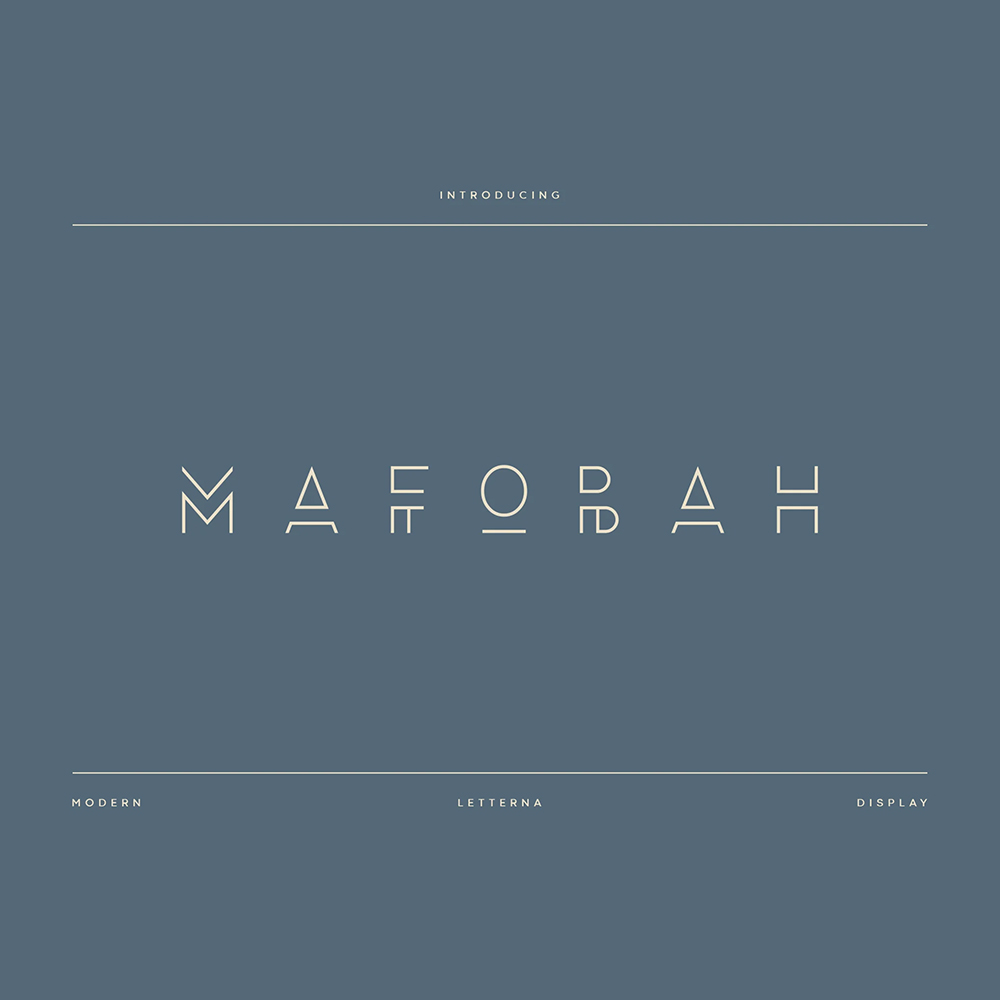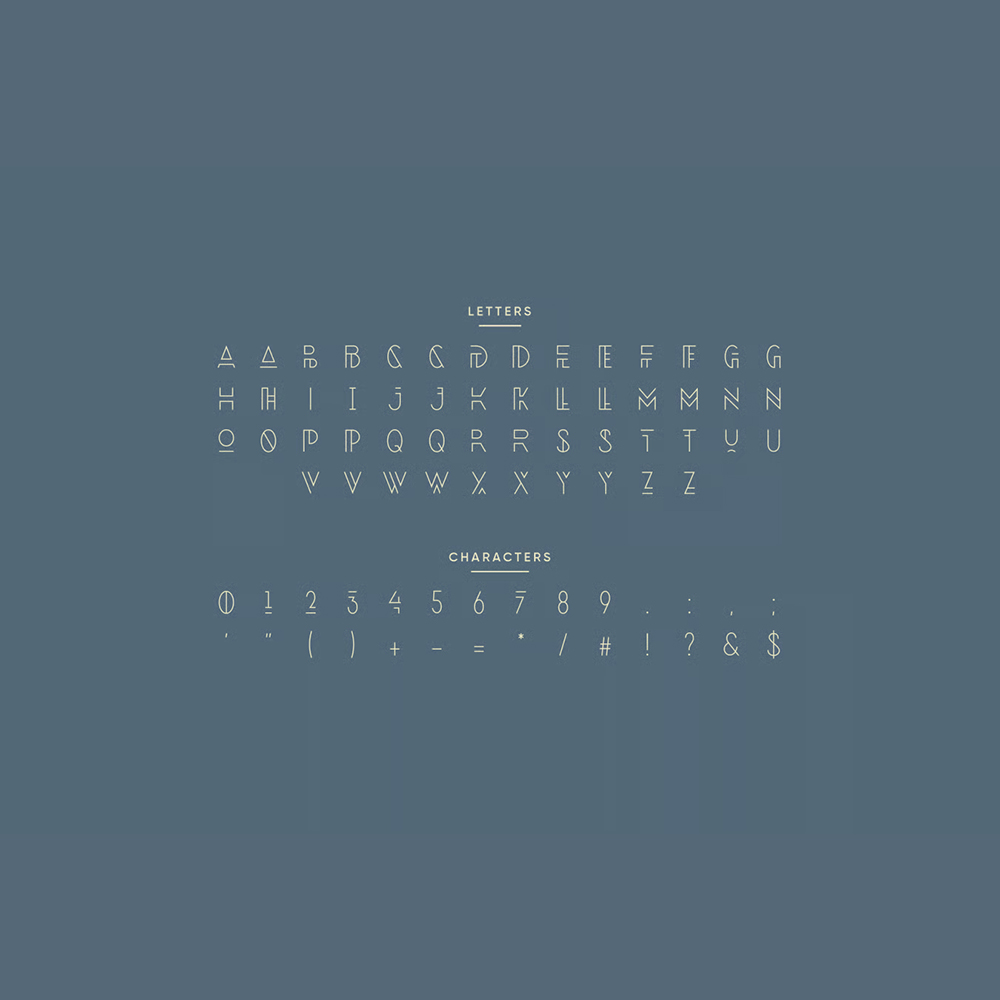
دانلود فونت انگلیسی Mafobah Font
فونت پرمیوم و انگلیسی Mafobah یک فونت زیبا که از روندهای فعلی در تایپوگرافی تیترهای دیجیتال الهام گرفته شده است سبکی بسیار مدرن و لوکس، منحصر به فرد است. قطعات هندسی زیبا برای انواع مختلف طرحها، لوگوهای بستهبندی محصول، طرحهای مد و طرحهای آینده عالی خواهند بود. میتوانید از آنها در طرحهای آیندهنگرانه یا بازی استفاده کنید.